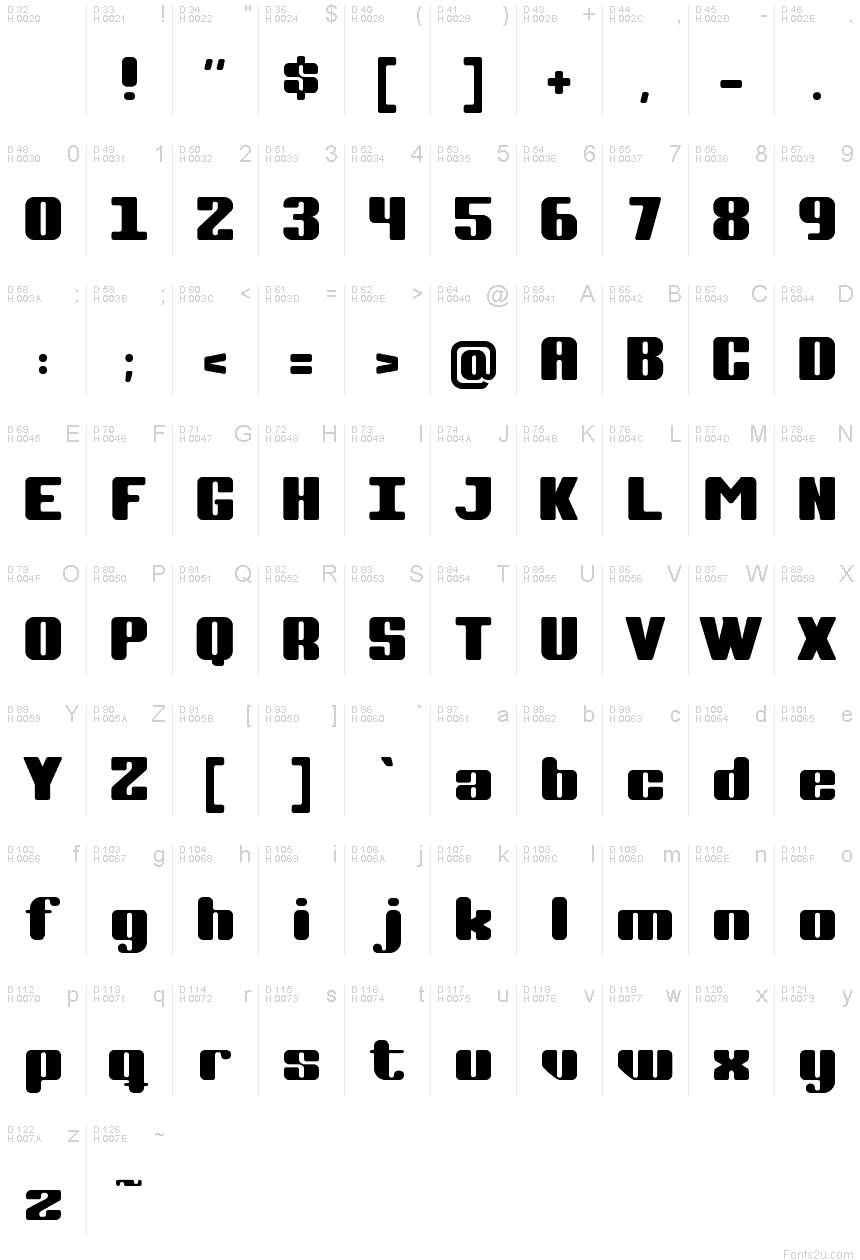
Complete Plain od Hreggvidur Arsaelsson je bezplatné, moderní displayové písmo, které promění každé slovo v odvážný, modulární blok. Těžké, zaoblené obdélníky do sebe zapadají jako dílky retro-futuristické skládačky, zatímco rovné vertikální řezy udržují texturu čistou a překvapivě dobře čitelnou. Rytmus pevných pruhů a hladkých rohů dodává vašim nápisům masivní, až hravý vzhled, který přesto působí ostře a záměrně.
Complete Plain vynikne na sci-fi plakátech, herních titulech, technologickém brandingu, výrazných logotypech, letácích na akce a poutavé grafice na sociální sítě. Její kompaktní, vzpřímené tvary milují velké velikosti, kde ty vyřezávané mezery a pevné tahy mohou skutečně dýchat. Zkombinujte ji s lehkým geometrickým bezpatkovým písmem pro hlavní text a získáte silný, současný kontrast, který zůstane ucelený.